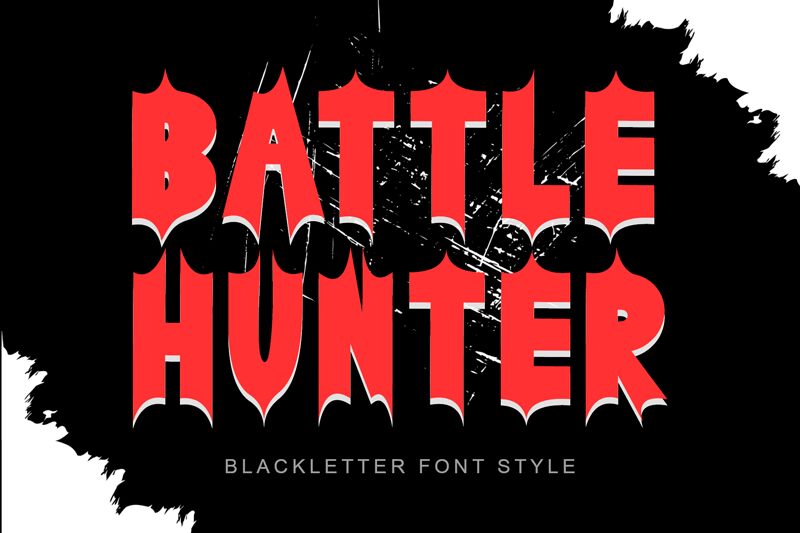
Battle Hunter
Battle Hunter, diseñada por Yoga Letter, es una tipografía gótica gratuita con cortes afilados y curvas internas redondeadas que otorgan a las letras una forma agresiva y tallada. Sus trazos son compactos y pesados, pero sin perder ese toque decorativo, mientras que las puntas repetidas en la parte superior e inferior crean un ritmo tenso en la composición.
Battle Hunter destaca en carteles de bandas de metal, títulos de videojuegos, logotipos de fantasía, diseños de tatuajes y portadas de álbumes donde se busca una estética gótica oscura. Esta fuente gratuita también funciona muy bien en titulares, folletos, merchandising y acentos gráficos, gracias a su silueta angular que transmite una personalidad arrolladora desde el primer vistazo.